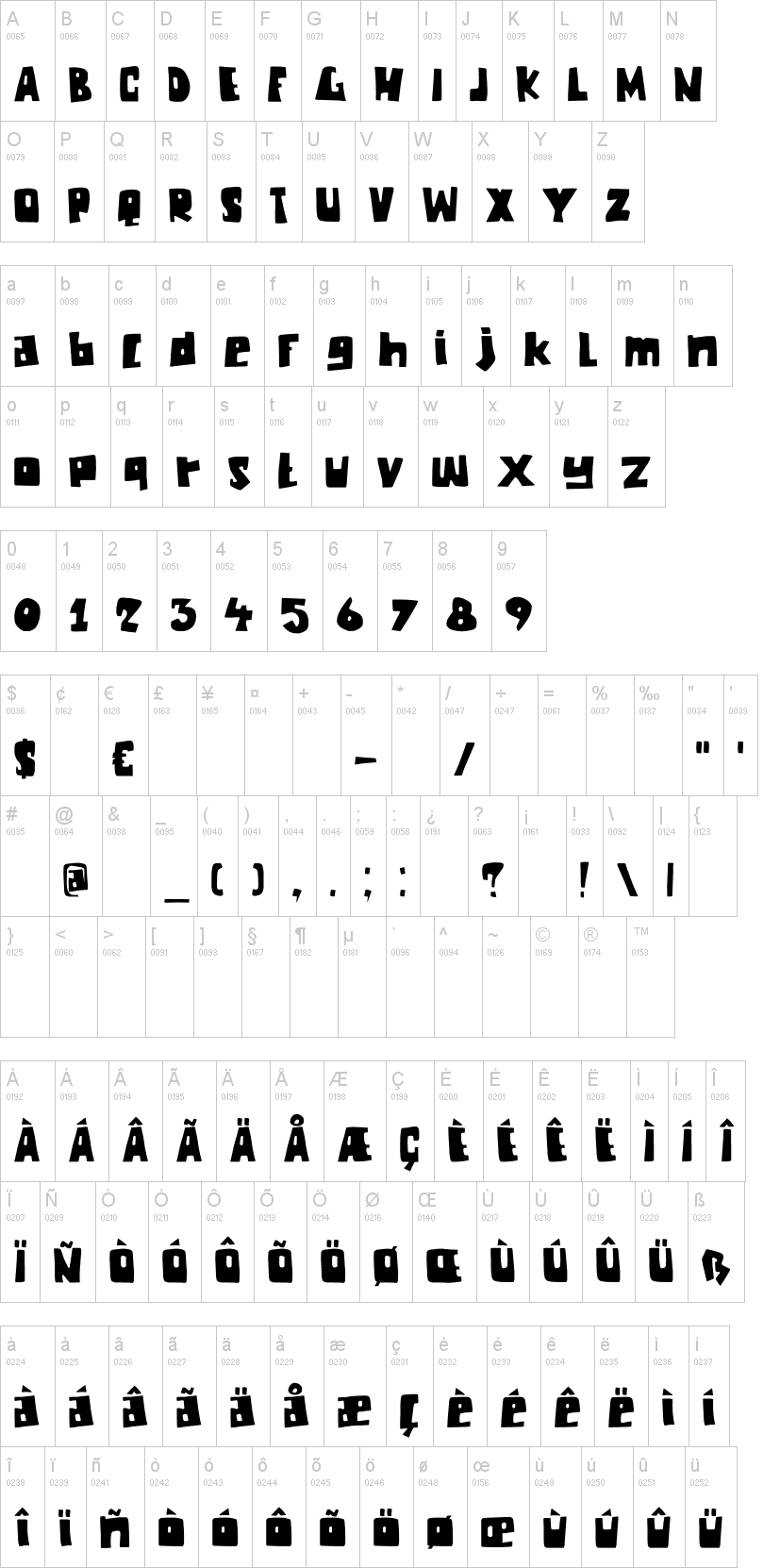
DK Chunky Chicken 字体是一种非常有趣和独特的手写风格字体,适用于许多不同的场合。这种字体的主要特点是它非常粗犷,字母之间有大量的空隙和松散的线条,使其看起来非常有活力和自信。此外,字母的外形也非常的简洁明了,易于阅读和理解。 这种字体适用于很多场合,如卡通、漫画、广告和海报等。由于其有趣、独特和易于辨认的特点,它非常适合用于各种儿童相关的设计和项目中,如儿童书籍、游戏、玩具和服装等。同时,它也可以用于设计食品相关的项目,如餐厅、食品博客和食品包装等。 总之,DK Chunky Chicken 字体是一种非常有趣、独特和多功能的字体,适用于许多不同的场合。内容介绍
DK Chunky Chicken是一款非常不错的手写艺术字体,具有很好的视觉感,适合于文化类的宣传设计、商业类品牌的广告和产品包装设计以及个性化文字排版等较多场景。